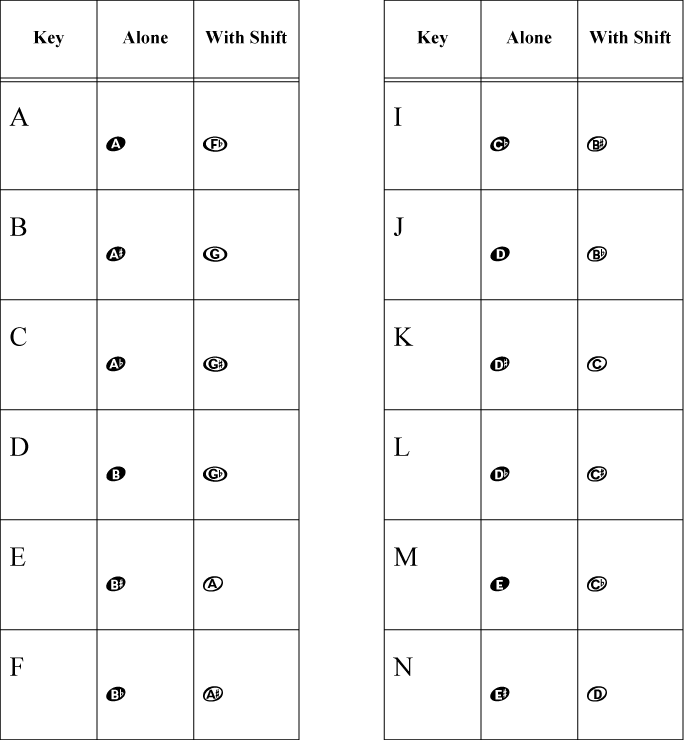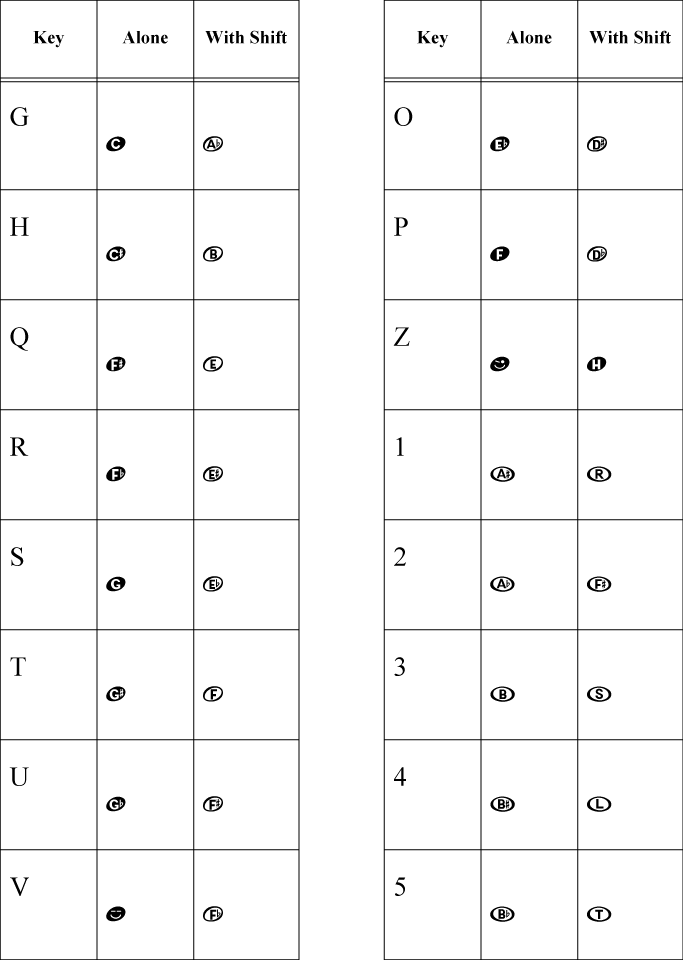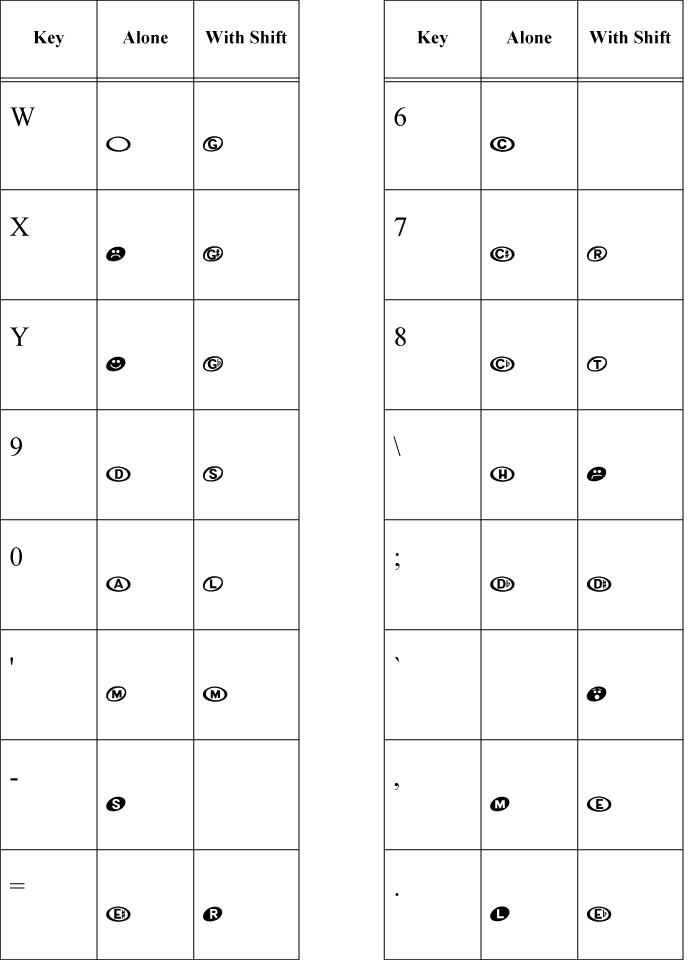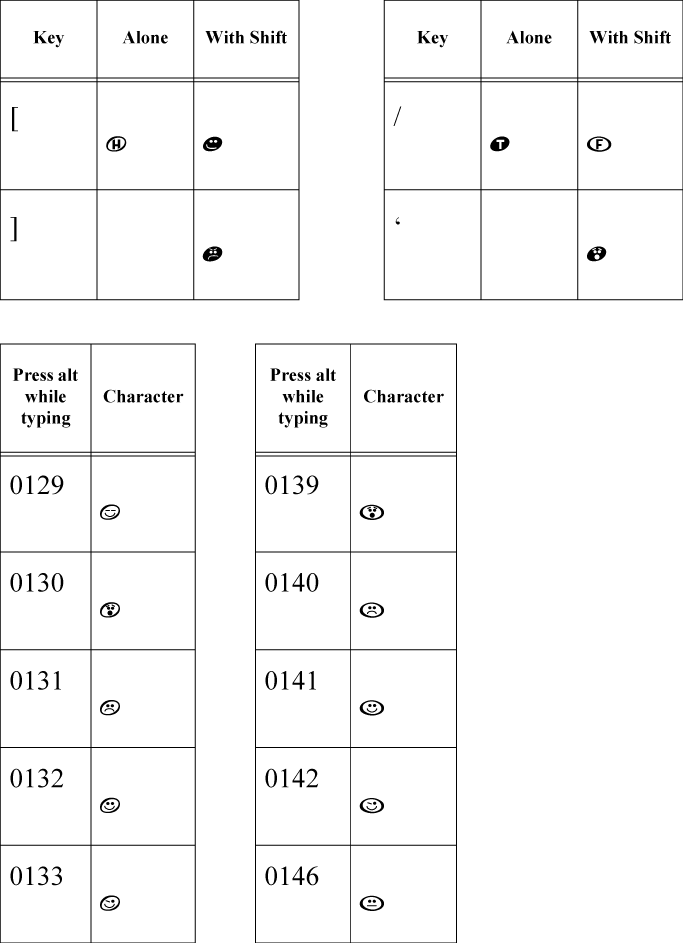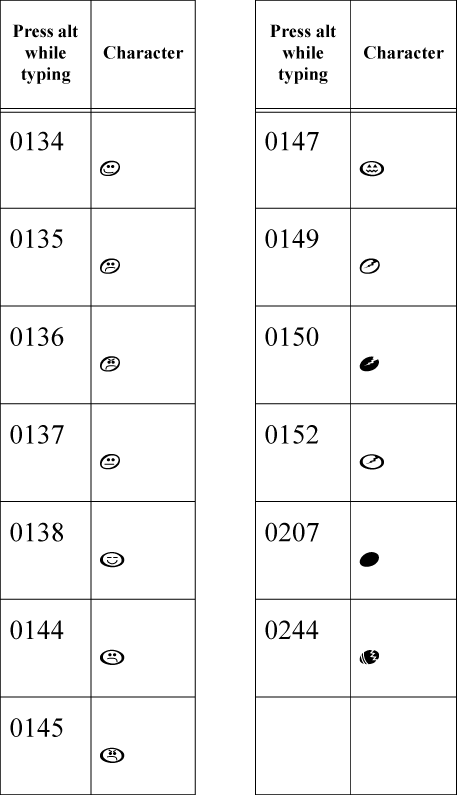
Il font Finale AlphaNotes è stato ideato per essere utilizzato dagli studenti di musica. La caratteristica di questo font è quella di posizionare il nome delle note all'interno delle teste delle note stesse. Se create un documento utilizzando uno dei modelli AlphaNotes (si trovano nella cartella Finale 2011/Music Files/Modelli), il file verrà automaticamente predisposto per adottare questo carattere. Potete anche assegnare questi caratteri alle teste delle note di tutta la partitura o di un solo rigo manualmente, utilizzando, rispettivamente la finestra di dialogo Opzioni del documento - Note e pause e la finestra di dialogo Forma delle teste delle note.
Per applicare questi caratteri alle teste delle note (come le note con il sorriso) seguite la procedura indicata:
Set di caratteri del font Finale AlphaNotes